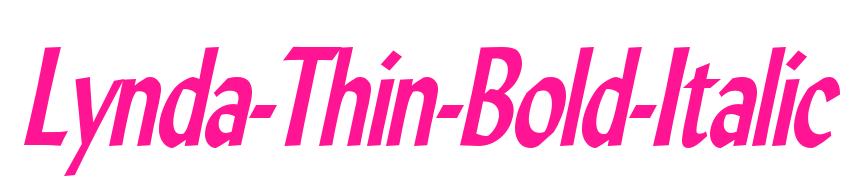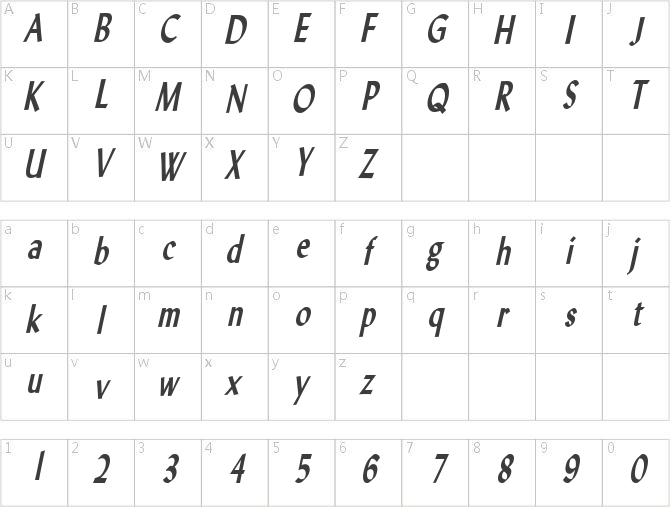
Lynda-Thin-Bold-Italic 詳情頁(yè)
Lynda-Thin-Bold-Italic字體字庫(kù)是一款讓人賞心悅目、百看不厭的英文字體,適合各類廣告和產(chǎn)品包裝設(shè)計(jì)應(yīng)用,字體大小0.05MB,格式為ttf字體,上傳用戶是翰池書法,作者/版權(quán)方為未知